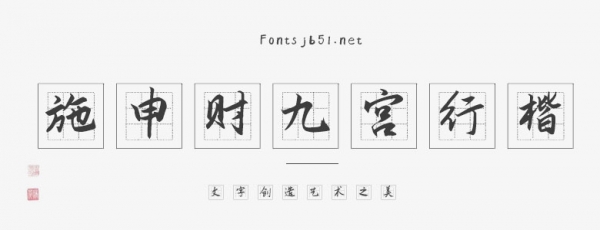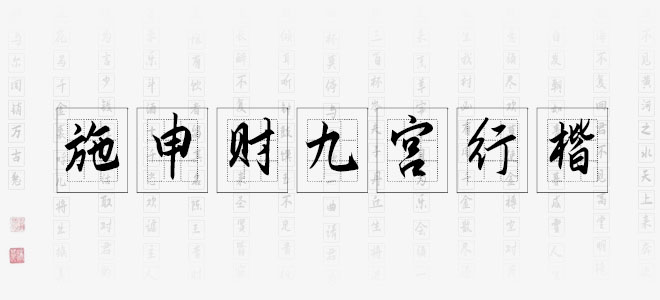
施申財(cái)九宮行楷是一款自帶九宮格背景效果的書法藝術(shù)字體,具有強(qiáng)烈的視覺(jué)沖擊力。適用于海報(bào)、電商海報(bào)設(shè)計(jì)、店鋪設(shè)計(jì)、標(biāo)志設(shè)計(jì)、字體設(shè)計(jì)等領(lǐng)域。
施申財(cái)九宮行楷